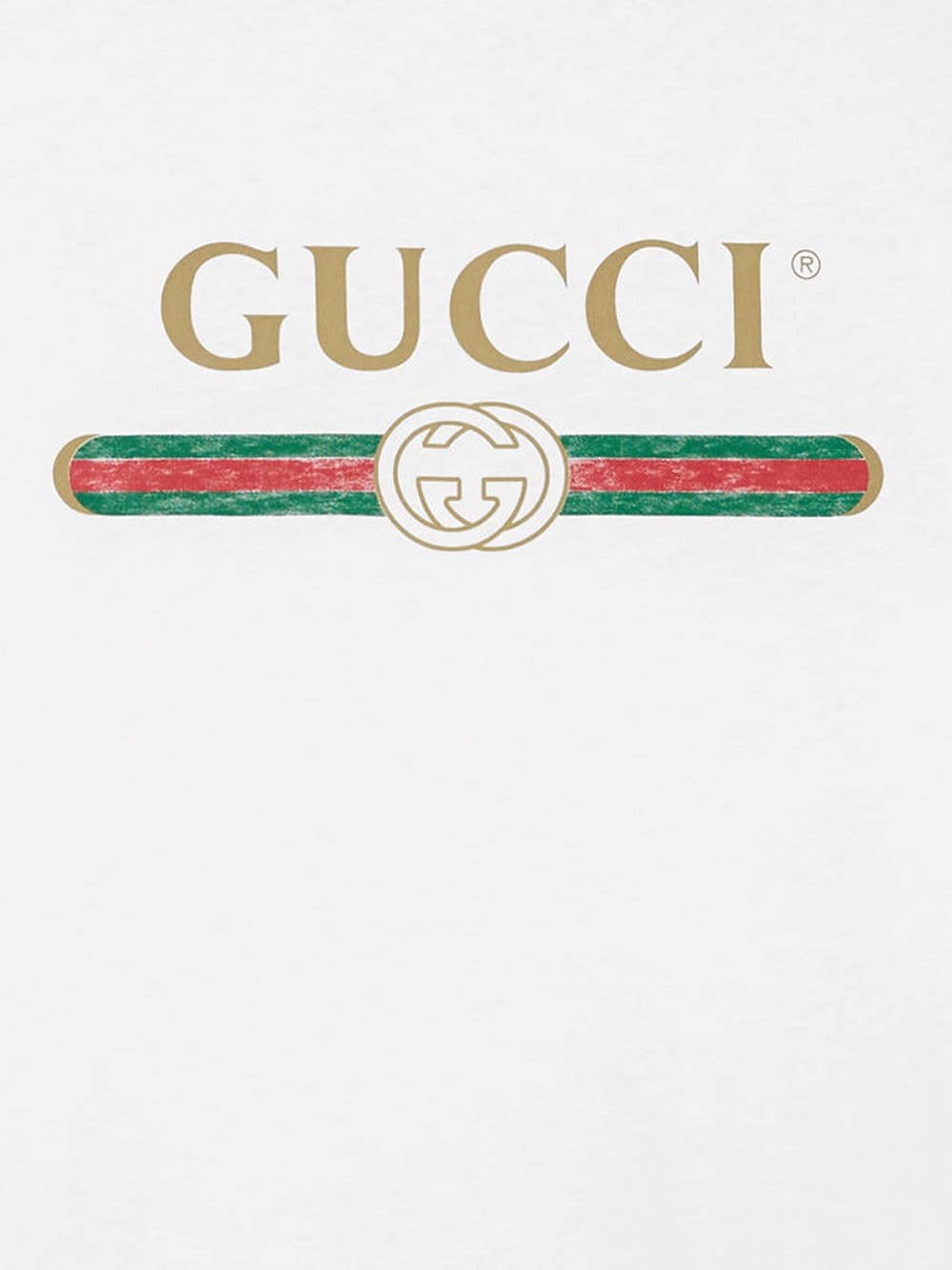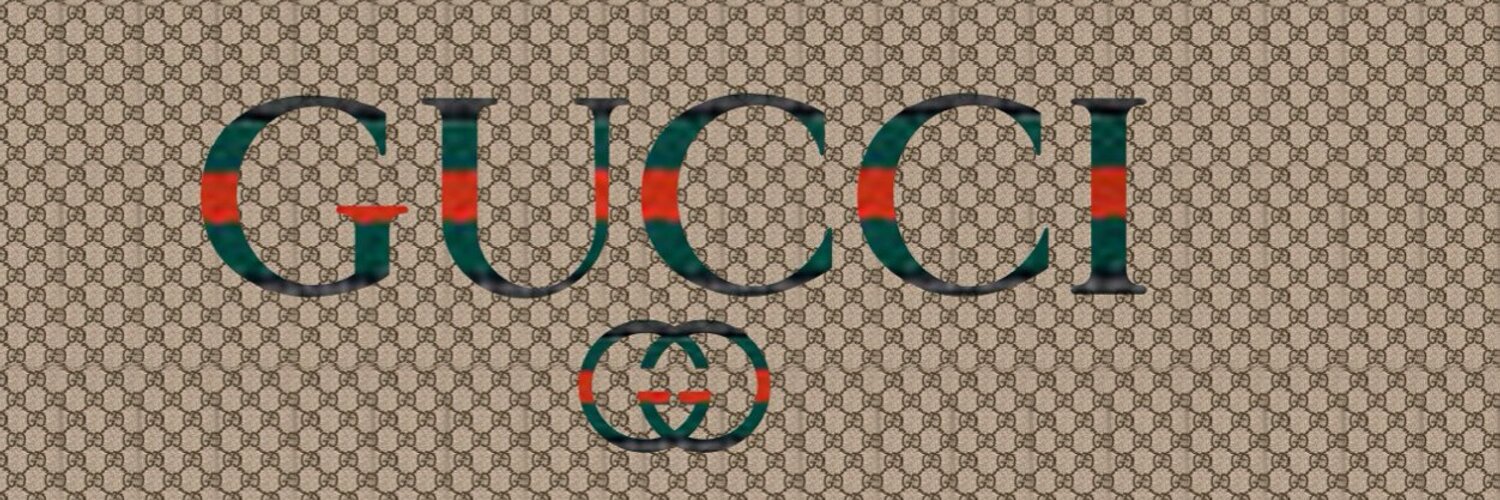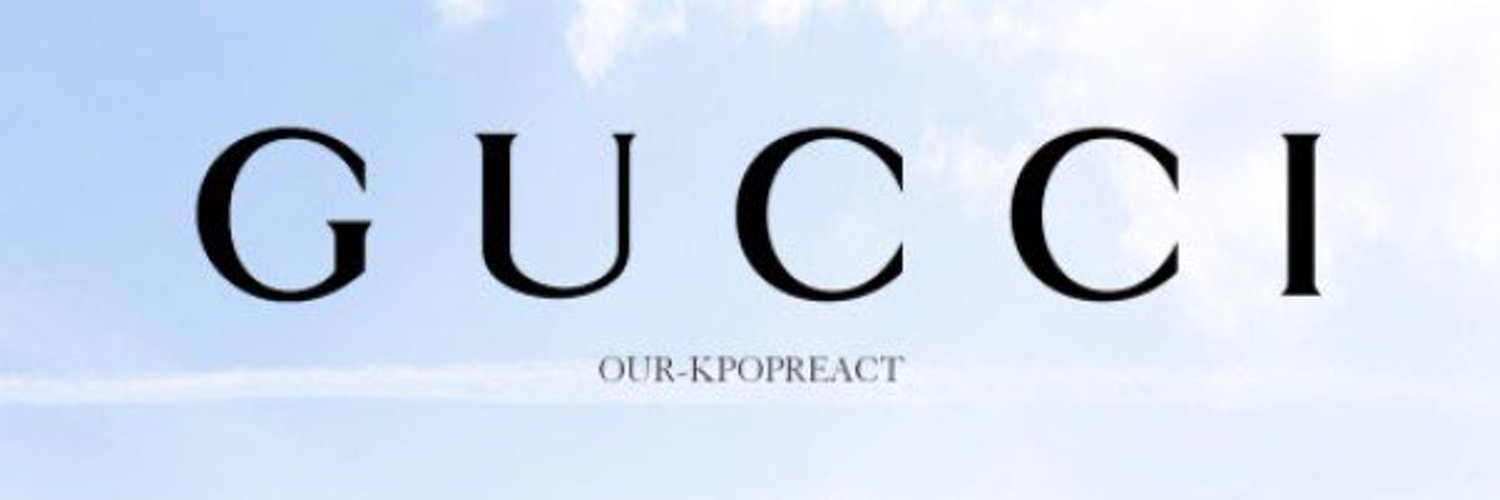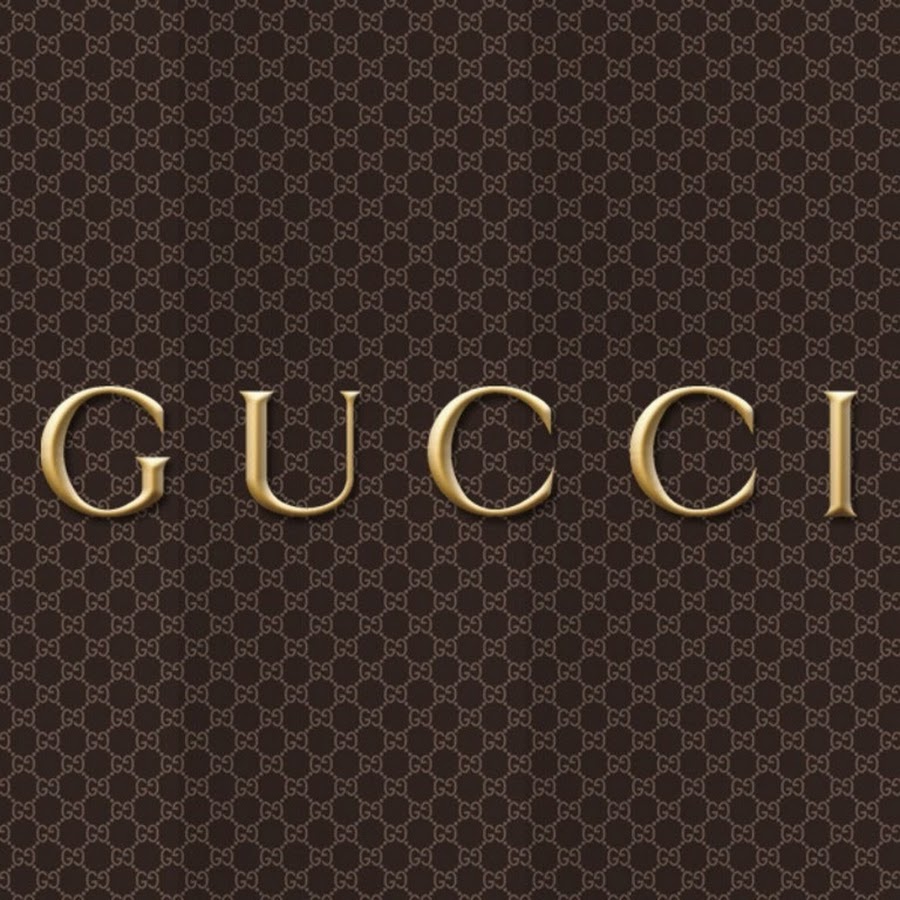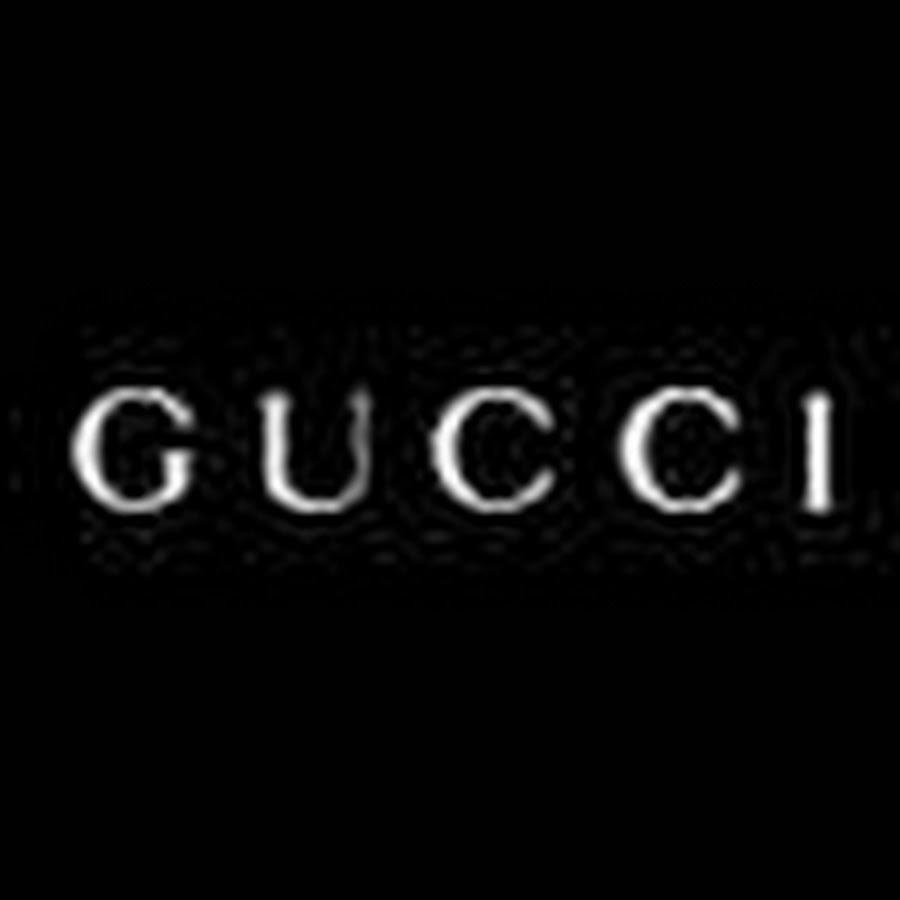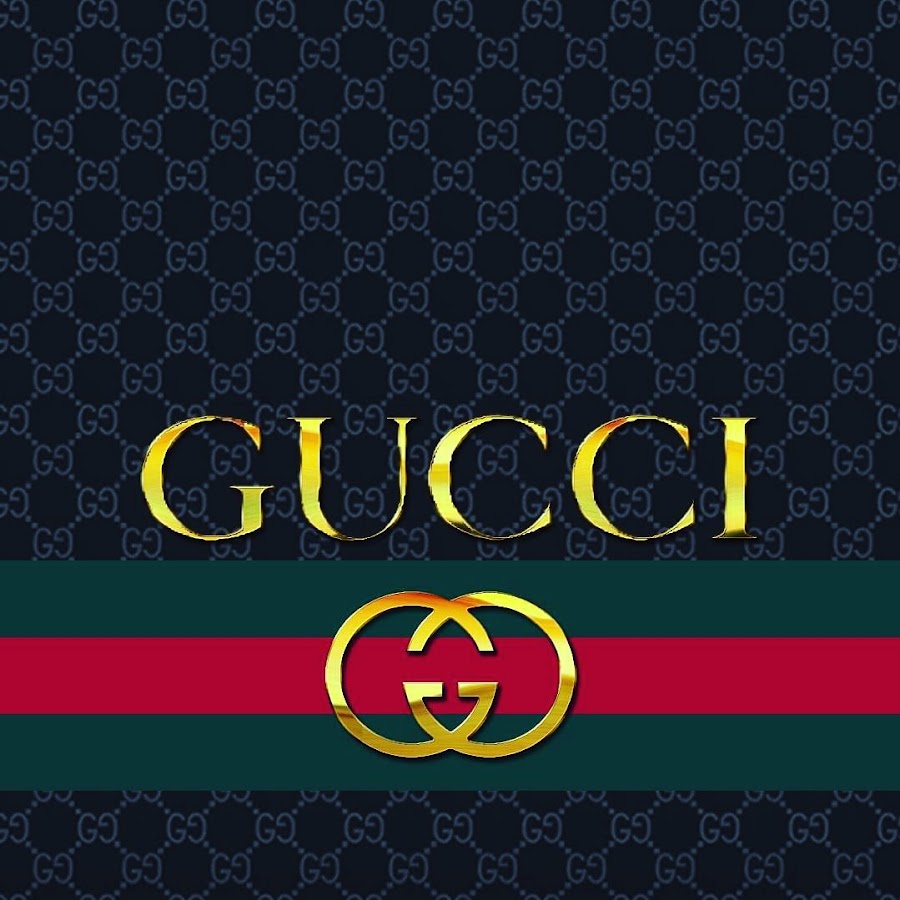
История логотипа Гуччи: развитие и эволюция бренда | Дизайн, лого и бизнес
Гуччи – популярный итальянский бренд, специализирующийся на изготовлении предметов одежды, парфюмерных композиций и аксессуаров. В настоящее время фирма является одной из крупнейших корпораций (не только в Европе, но и в мире) по созданию и реализации модных товаров различного вида.
Дом моды Гуччи основал Гуччио Гуччи (Флоренция, 1904 год). Предпосылкой явился любопытный факт из биографии мужчины: в молодости он работал официантом ресторана одного из известных лондонских отелей, где постоянно обращал внимание на кожаные сумки и чемоданы отдыхающих.
Изделия произвели на него такое сильное и яркое впечатление, что после возвращения на Родину, Гуччио открыл собственную мастерскую. В ней он изготавливал чемоданы, сёдла и сапоги для верховой езды.
1938 год ознаменовался началом работы фирменной торговой точки в Риме. А в 1947 году бренд выпустил первую дамскую сумку, ручки которой были сделаны из бамбука.
В 1950-х производство компании расширилось, и фирма стала выпускать текстильные полотна с узорами и мокасины из замши.
Первый логотип Гуччи
История логотипа Гуччи началась в год основания компании. Изначально, в 1920-х годах Gucci логотип был контурным. Он состоял из чёрно-белого изображения небольшого носильщика. В одной руке персонажа находится саквояж, а в другой – чемодан (сохранилось всего несколько фото логотипа Гуччи тех времён). Иногда юноша изображался в виде рыцаря в доспехах (всё с теми же изделиями в руках) и становился частью герба. Эмблема помещалась на все производимые товары.
Кто создал логотип Гуччи
Лого с двойным символом «G» появился только в 1933 году. Его автором был один из трех сыновей Gucci, Альдо Гуччи. Именно он поместил на фирменный знак инициалы своего отца.
История изменения логотипа Гуччи
Спустя несколько лет лого Гуччи стали украшать серебряными и золотыми элементами – символ хранил память об отеле, работа в котором стала для Гуччио Гуччи судьбоносной.
Во время Второй мировой войны возникли сложности с ввозом немецкой кожи. Это поставило работу компании под угрозу, так как преимущественно при производстве товаров использовалась именно она. Вследствие этого основатель бренда принял решение договориться с поставщиками неаполитанской конопли, которой должна была заменяться кожа. Этот материал схематично обозначался тёмно-коричневыми ромбами. Так сформировался ещё один, «текстильный» логотип Гуччи.
1970-е
Зелёный и красный оттенки появились и 1970-х и были зарегистрированы в качестве элемента товарного знака бренда. Однако данный вариант логотипа просуществовал недолго, до 1933 года.
1993
В 1993 году появляется современный вид логотипа Гуччи. Он представляет собой две заглавные буквы «G», символизирующие инициалы Гуччио Гуччи. Кроме того, они имеют необычное расположение: развернуты друг к другу и переплетены между собой.
Над буквами располагается фамилия создателя марки. Надпись выполнена заглавными буквами рубленным шрифтом.
Известно, что такой эскиз разработал старший сын родоначальника компании.
Нередко можно встретить на продукции фирменные знаки несколько иного дизайна. Иногда они окрашиваются в золотой оттенок, но также используется исполнение эмблемы в чёрном цвете.
Всемирно известный Gucci логотип – неотъемлемая часть современных, качественных и красивых изделий. Сегодня носить вещь с этой оригинальной эмблемой – признак достатка и превосходного вкуса.
Часто задаваемые вопросы
Что означает символ на логотипе Гуччи?Двойной символ «G» – первые буквы имени и фамилии основателя компании Гуччио Гуччи.
Кто создал логотип Гуччи?Автором знака с двойной буквой «G» является сын основателя компании Альдо Гуччи.
Какой шрифт используется в логотипе Гуччи?Надпись на лого Gucci выполнена шрифтом Granjon Roman. Он в свою очередь произошел от шрифта Garamond.
Когда появился логотип Гуччи?Привычная нам версия лого Гуччи с двойной буквой «G» появилась в 1933 году.![]()
Как распознать оригинальный ремень Gucci
В 2015 году тогда еще мало известный дизайнер Алессандро Микеле был назначен креативным директором модного дома Gucci. Он не только возродил Gucci, но и радикально изменил днк бренда. Первым показом Алессандро была запущенна новая волна логомании. Позже ее подхватили многие люксовые бренды, стряхнув пыль со своих винтажных логотипов: от Dior, представившего сумку-седло с архивным логотипом, до Fendi со своим коронным принтом 1974 FF.
Культовой вещью с того самого первого показа Алессандро Микеле стал ремень с пряжкой в виде двойной буквы G — Gucci GG Marmont. Микеле использовал логотип, со всем уважением к 95-летней истории бренда, при этом вложил в него свою максималистскую эстетику — добавил цвета и игривые мотивы. Это сделало ремень современным и актуальным.
В целом, существует тенденция отдавать предпочтение стилю, а не функциональности, наряду с удивительным недостатком воображения, когда дело касается типографики. Есть фундаментальные проблемы с настройкой шрифта с точки зрения веса, цвета и размера. Многие макеты просто нечитаемы на экране (например, Burberry, Tiffany, Dior и Gucci). Использование бесплатных шрифтов является обычным явлением и противоречит роскошному имиджу. Бренд — это все, и хотя не каждый бренд увидит ценность в индивидуальном шрифте, при использовании Arial или Times нет разницы между высоким уровнем или бюджетом, особенно на мобильных устройствах, где очень мало места для изображений.
В первые годы существования бренда официального логотипа не существовало.